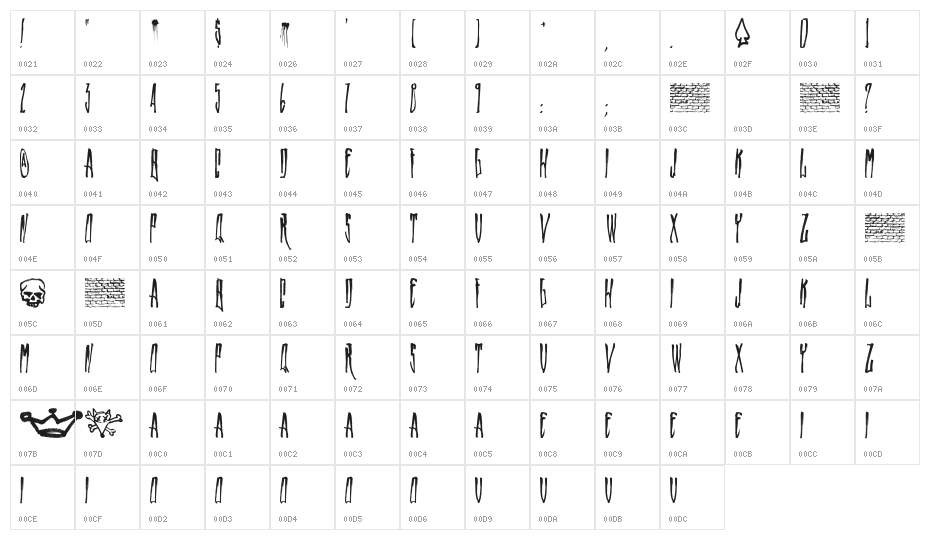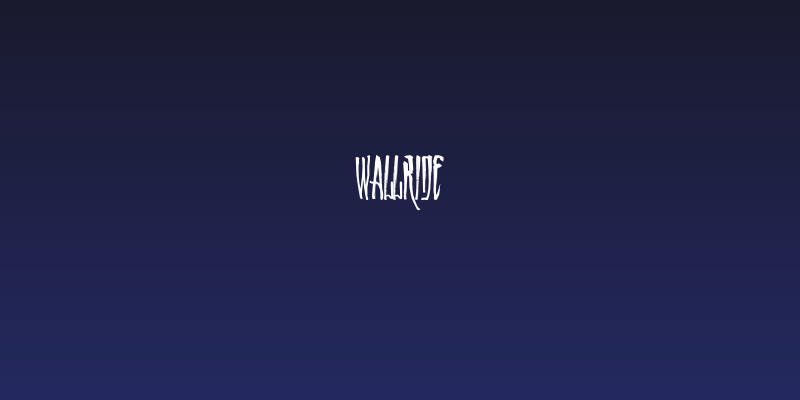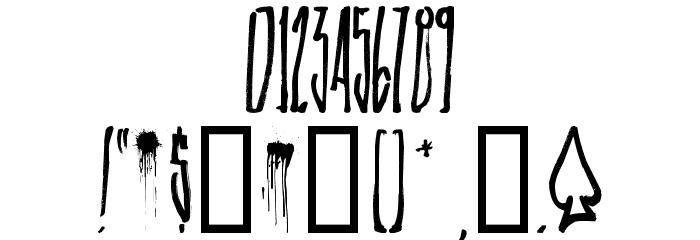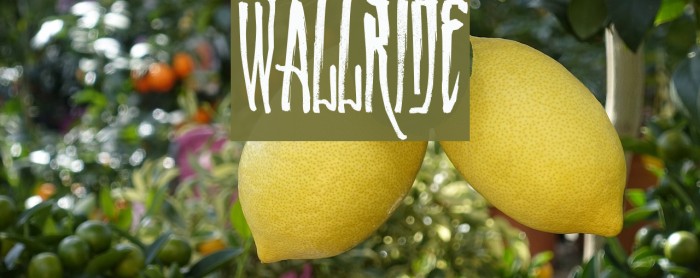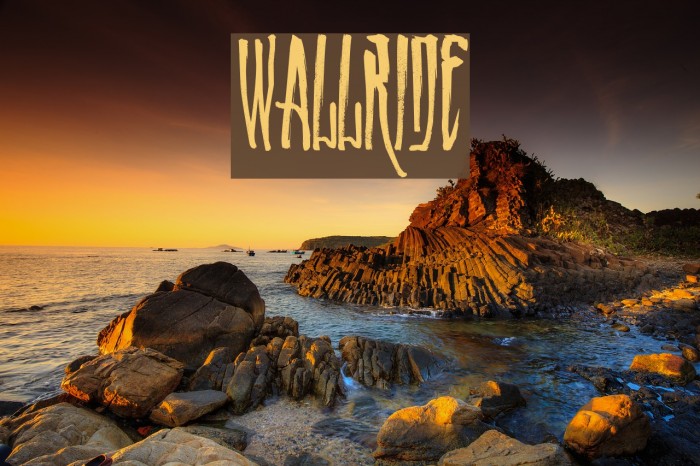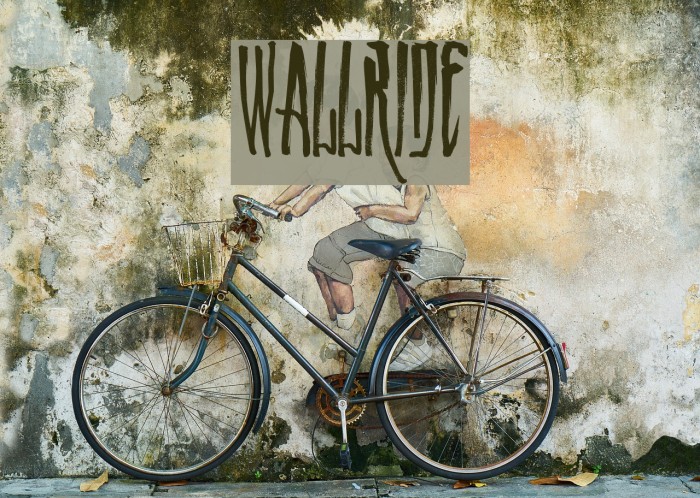
WALLRIDE Font
| Gesamtstil | Modern, Urban, Edgy |
| Vorgeschlagene Projekte | Ideal for street art designs, music album covers, urban-themed posters, and edgy branding projects. |